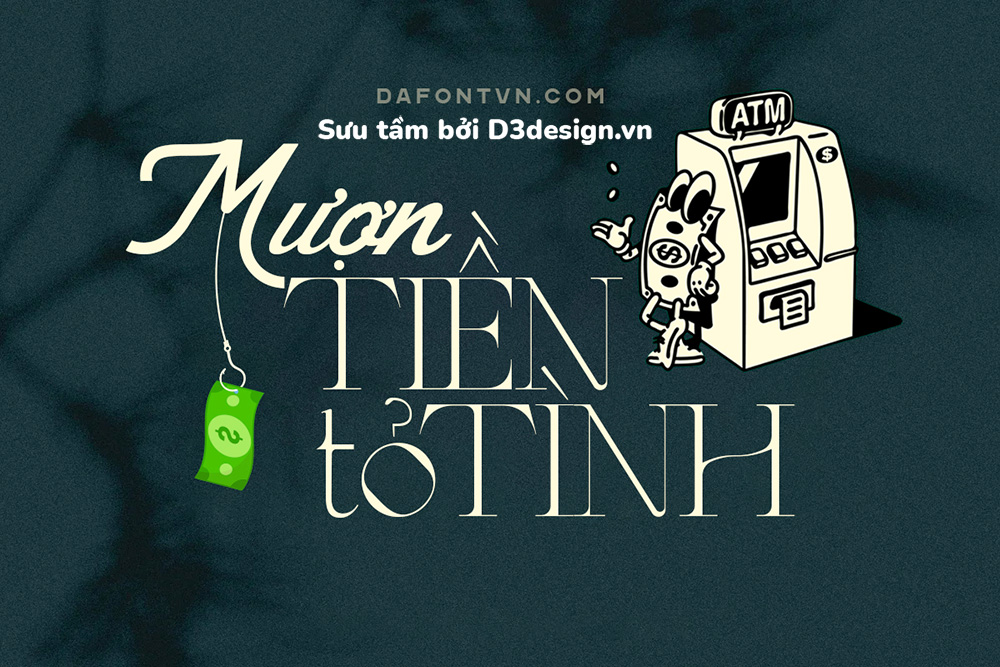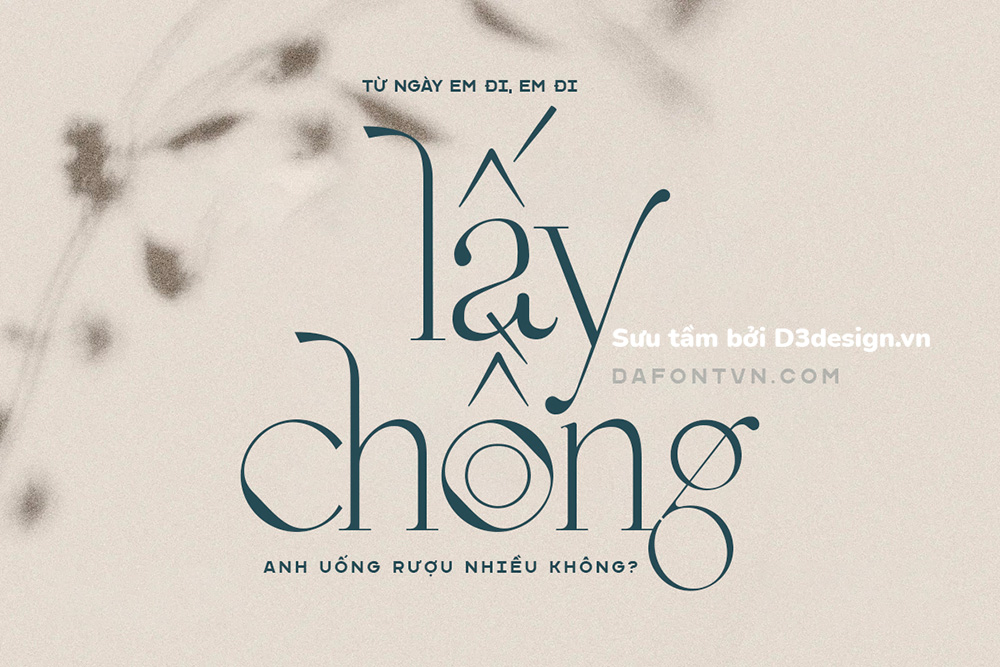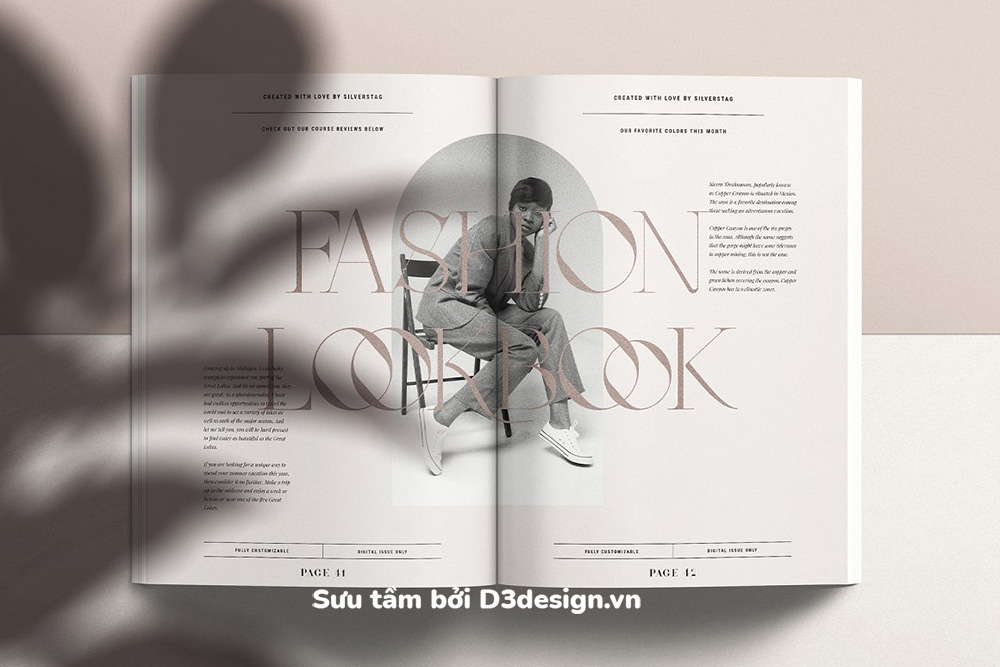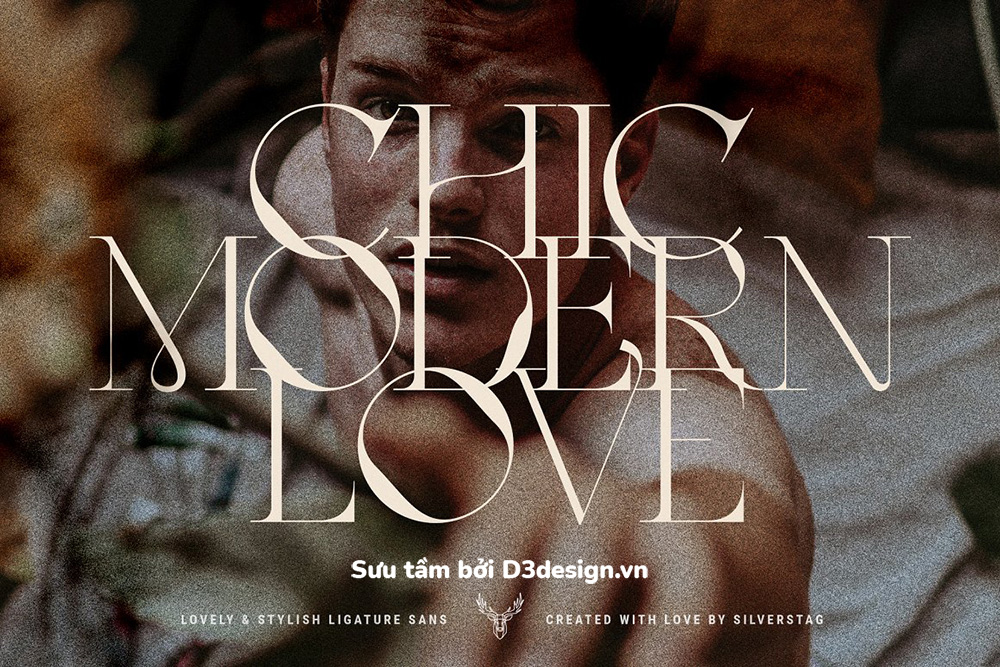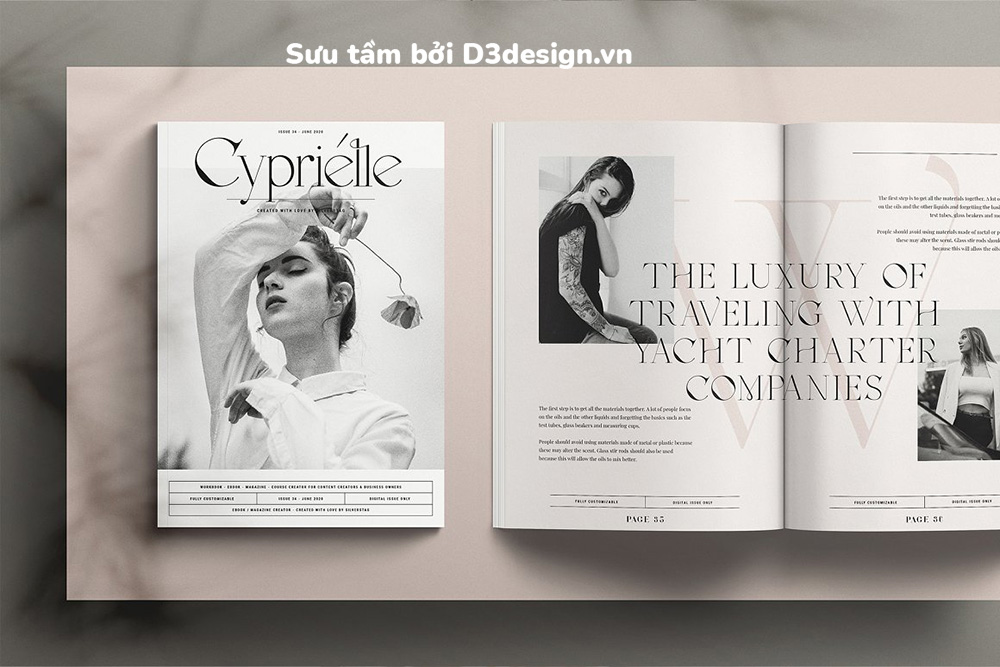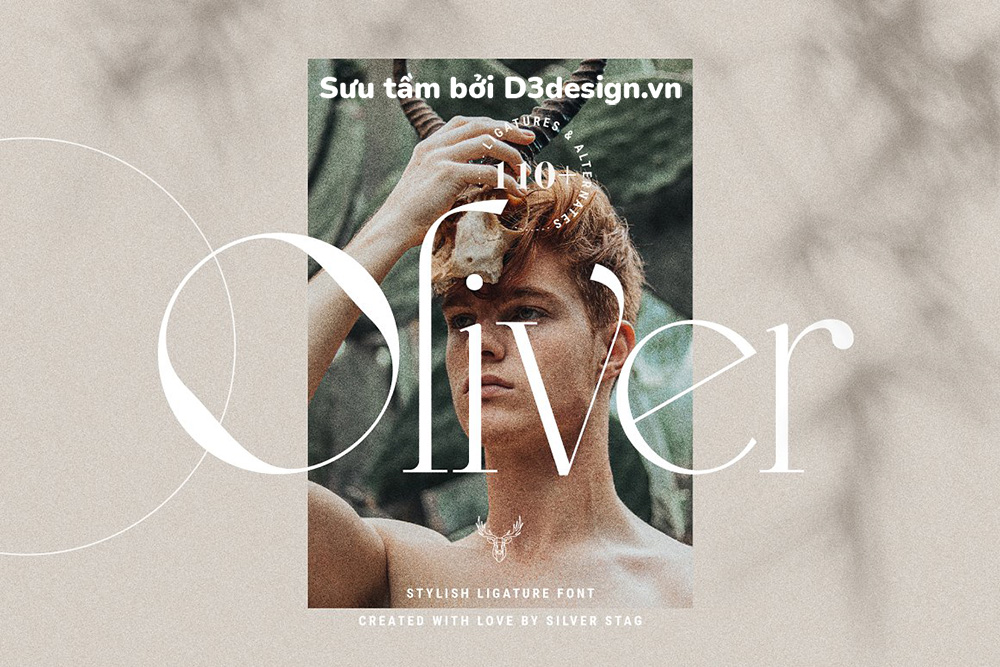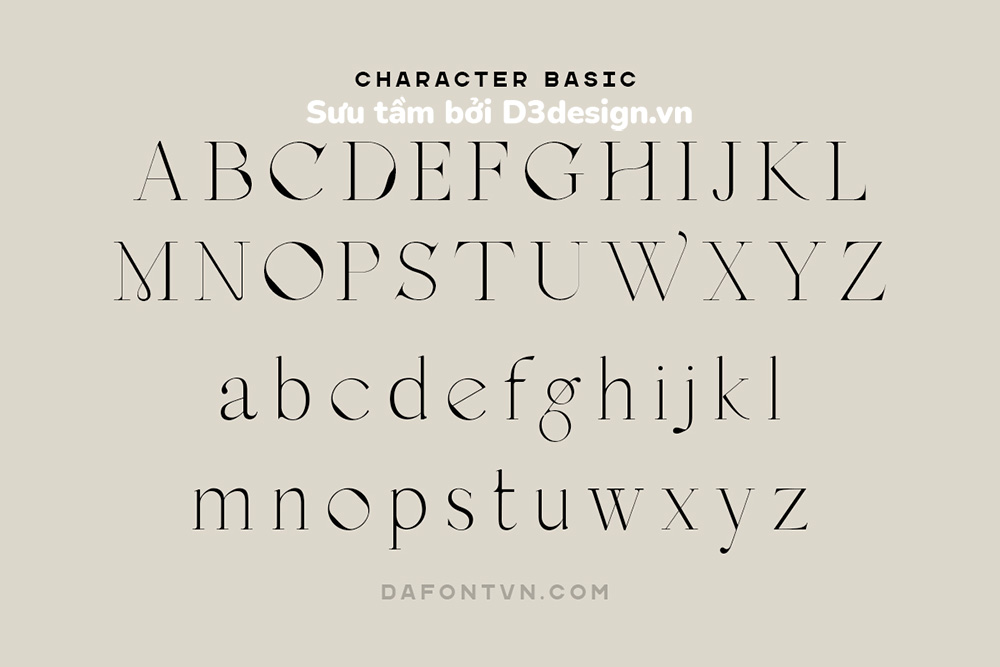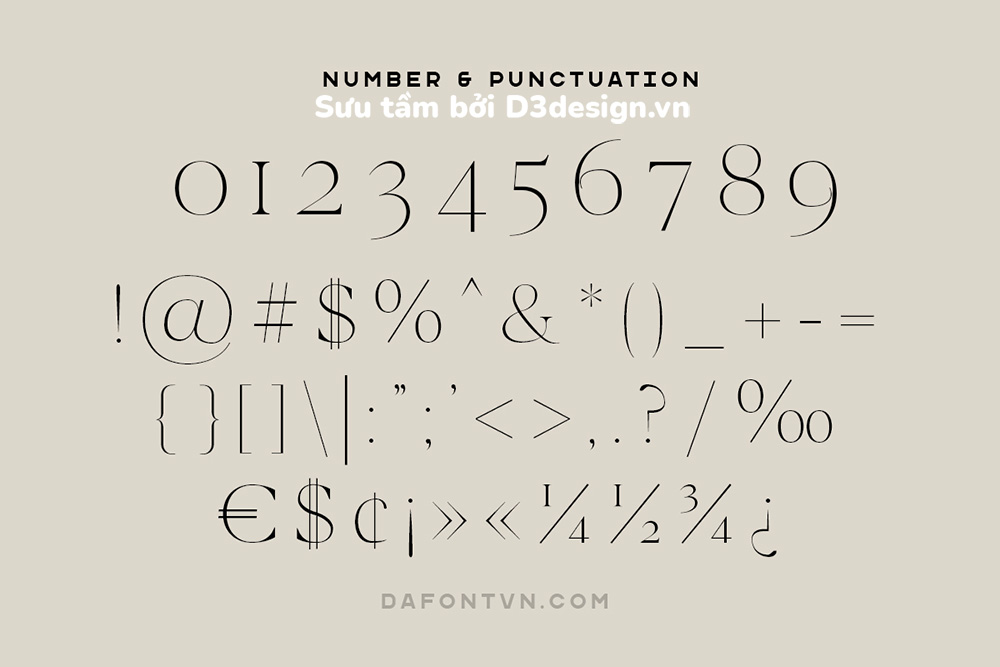
Font Việt Hóa - MOON CROWD Mang Phong Cách Sang Trọng Và Hiện Đại
MOON CROWD là một font chữ serif ghép nối hoàn toàn lấy cảm hứng từ vẻ đẹp và sang trọng cùng với các dấu nổi bật. Phông chữ sang troạng và hiện đại đi kèm với hơn 100 chữ ghép và các chữ cái thay thế. Mối chữ cái tiêu chuẩn, chữ ghép và các chữ cái thay thế được thiết kế thủ công. Tất cả các chữ cái đều độc đáo với các cạnh được bo tròn mềm mại.
Font MOON CROWD phù hợp cho nhiều thiết kế khác nhau với các thiết kế cần sự hoàn hảo trong các tiêu đề hiển thị, bìa sách, tạp chí, typography, thiệp cưới, quote...
Font MOON CROWD việt hóa được việt hóa đầy đủ, các dấu được chỉnh sửa, tối ưu lại để phù hợp hơn với các dấu Tiếng Việt.